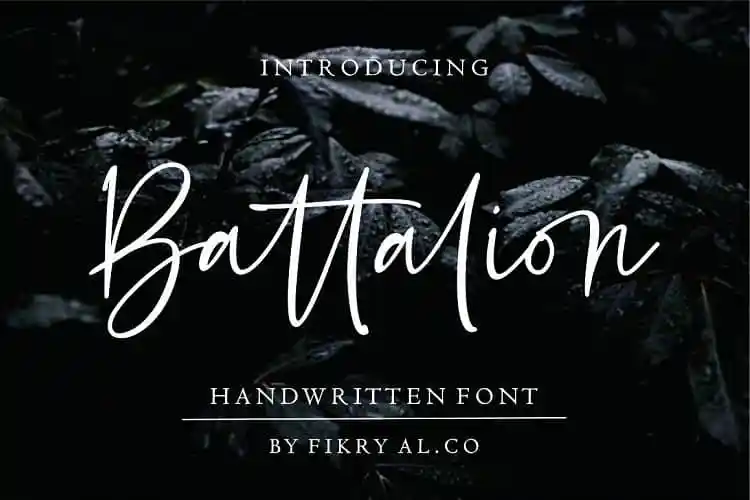
Battalion Handwritten Font – Download Grátis
Esta é uma fonte escrita à mão com estilo elegante e moderno, perfeita para letras que você deseja usar. É uma mistura arrojada e moderna de letra autêntica ideal para um grande número de aplicativos, como logos, marcas, citações, revistas, embalagens de produtos, assinaturas, banners, postais e muito mais. A fonte Battalion possui várias ligaturas e alternativas, o que a torna uma opção versátil em uma variedade de idiomas, incluindo francês, espanhol, alemão e outros. Seja você um designer, um profissional da imprensa ou apenas alguém que gosta de criar designs pessoais, Battalion está aqui para complementar sua estética sem fazer alterações significativas à sua identidade visual. Ele é perfeito tanto para projetos profissionais quanto para expressões mais pessoais. Aproveite a experiência única e elegante da Battailon Handwritten Font.